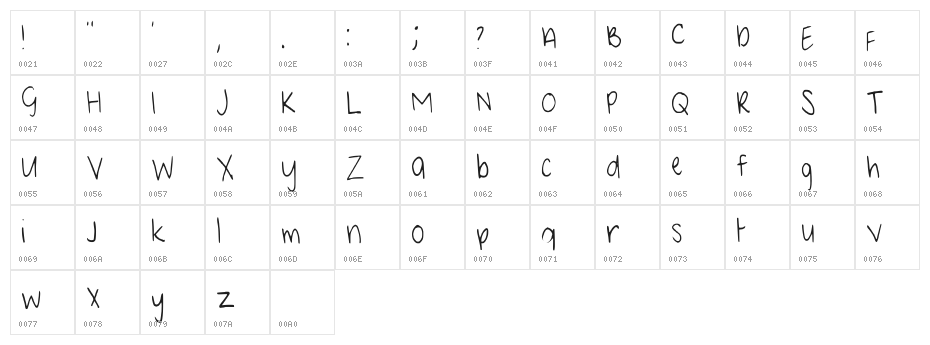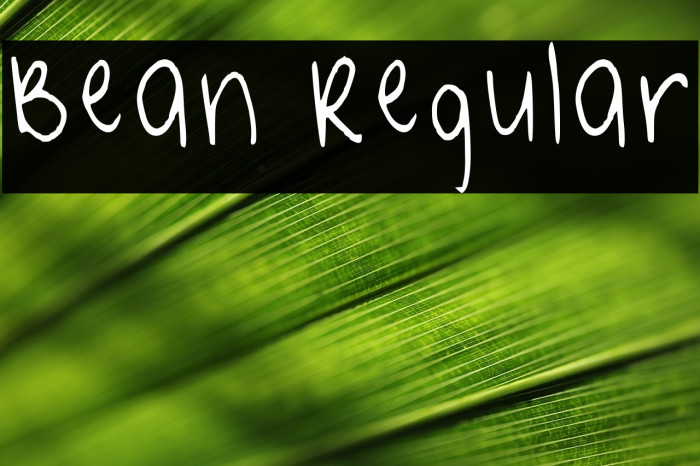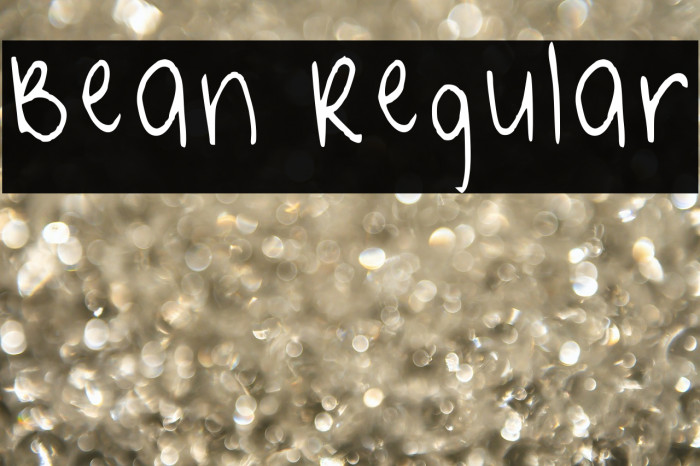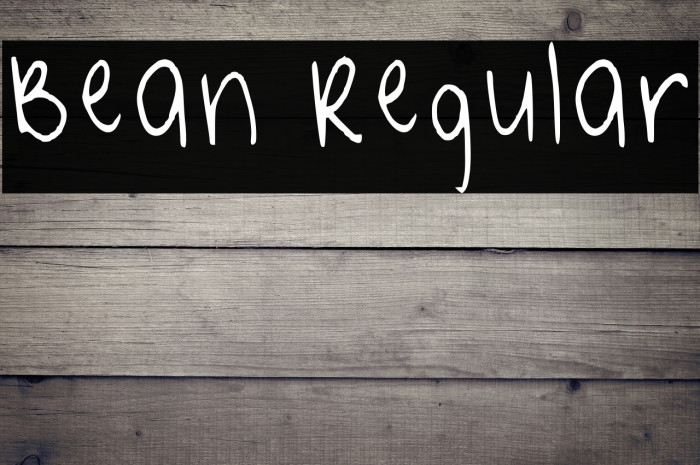
Bean Regular Font
| 全体的なスタイル | Casual, Playful |
| 用途 | Headlines, Informal text, Creative projects |
| おすすめプロジェクト | Ideal for greeting cards, children's books, casual branding, and social media graphics. |